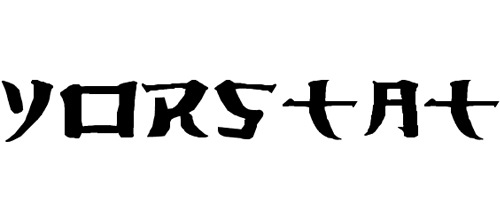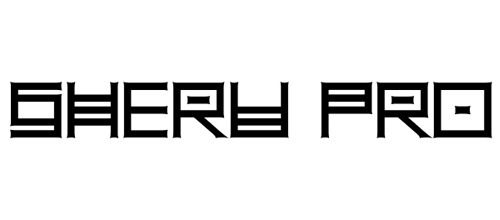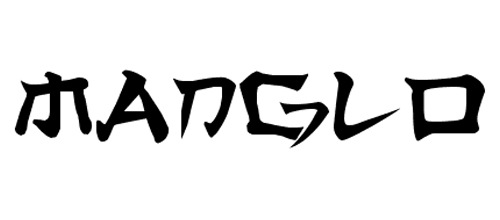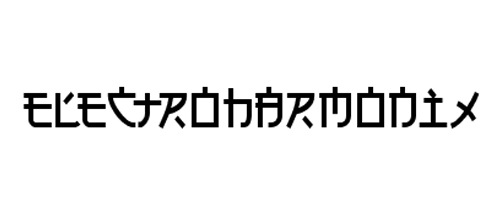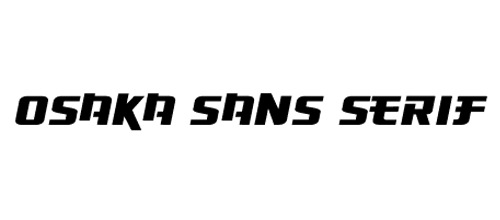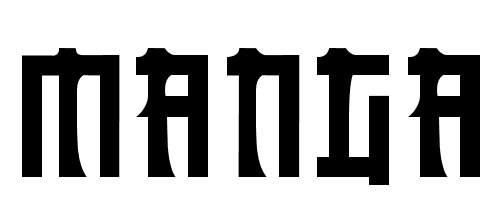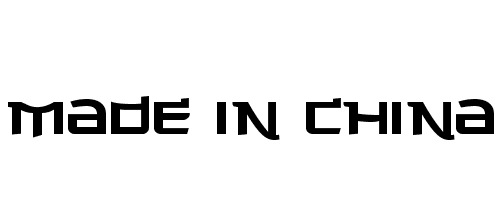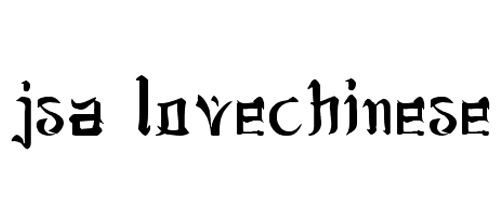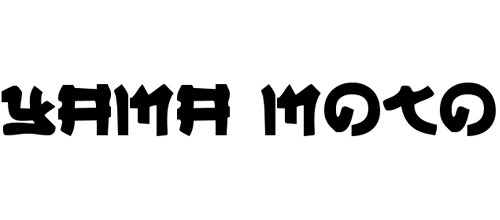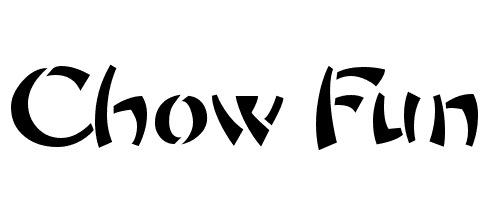
30 шрифтов в китайском стиле
шрифты-в-китайском-стиле Шрифты являются полезным ресурсом для любого дизайнера. С их помощью вы сможете придать определенный стиль и выразить смысл своей работы. В шрифтах, также как и в дизайне, есть множество направлений. Они могут быть простыми и чистыми, с потеками краски в стиле гранж, урбанистическими, восточными, фигурными и так далее.
В сети таких ресурсов великое множество, но на их поиски приходится тратить немало времени. В этой подборке, вам предоставлена возможность загрузить 30 шрифтов, выполненных в китайском стиле. Все они абсолютно бесплатны. С их помощью вы сможете преобразить любую работу, создание которой навеяно “Китайским Новым Годом”!
Шрифт Chow Fun
округлый шрифт
Shanghai шрифт
шанхайский шрифт
Шрифт под названием Karate
карате шрифт
Техничный шрифт Technojap
техничный шрифт
Милый шрифт Cute Line
забавные буквы
Шрифт в китайском стиле Hirosh
шрифт в китайском стиле
Аккуратный шрифт в китайском стиле Gang of Three
аккуратный шрифт
Шрифт в стиле набросков Takeout
шрифт в стиле набросков
Чистый каллиграфический шрифт Wonton
каллиграфический шрифт
Шрифт в каллиграфическом стиле Yorstat
шрифт в каллиграфическом стиле
Креативный угловатый шрифт Sheru Pro
креативный угловатый шрифт
Необычный шрифт Manglo
китайский шрифт
Шрифт Electro в виде иероглифов
шрифт в виде иероглифов
Шрифт Osaka Sans
шрифт в спортивном стиле
Manga шрифт
шрифт манга
Шрифт Made in China
сделано в китае
Узорный шрифт Love Chinese
узорный шрифт
Креативный шрифт Yama Moto
Креативный шрифт
Крупный жирный шрифт Nuku Nuku
крупный жирный шрифт
Крупный китайский шрифт Chinyen
крупный китайский шрифт
Тонкий шрифт Shai
тонкий шрифт
Шрифт Chang Chang
рваный шрифт
Заглавный шрифт в китайском стиле Tsa
Заглавный шрифт в китайском стиле
Четкий равномерный шрифт Light Morning
четкий равномерный шрифт
Контурный шрифт Ninja Line
Контурный шрифт
Крупный жирный шрифт Ginko
крупный жирный шрифт
Китайский изогнутый шрифт Deng Thick
китайский изогнутый шрифт
Жирный угловатый шрифт Rufcut
Жирный угловатый шрифт
Жирный шрифт Seven Monkey
жирный шрифт
Шрифт в стиле дальнего востока Far East
шрифт в стиле дальнего востока